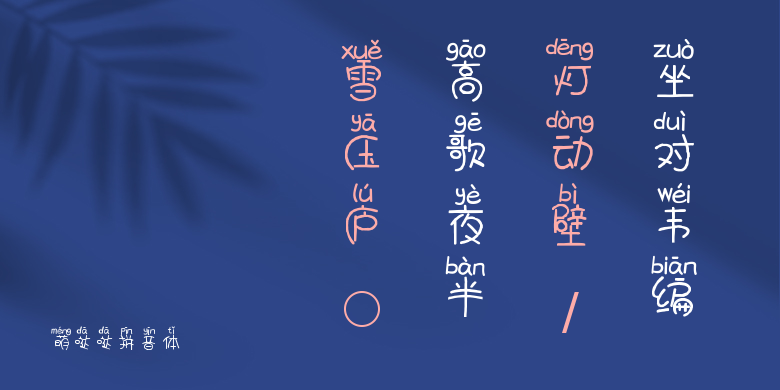
萌哒哒拼音体
萌哒哒拼音体,这款字体结构工整、笔画清晰,兼顾美观与易读性,适用于标题、正文、海报、包装、LOGO 等多种场景。字形优雅稳定,风格百搭耐看,适配日常排版与创意设计,让文字呈现更舒适、更具质感。萌哒哒拼音体一笔一画,皆是细节,以均衡的比例、流畅的线条打造舒适视觉体验,字形端正大气,风格简约现代。无论是商业设计、品牌宣传还是日常排版,都能轻松驾驭,让文字更有格调与力量。萌哒哒拼音体字体下载。